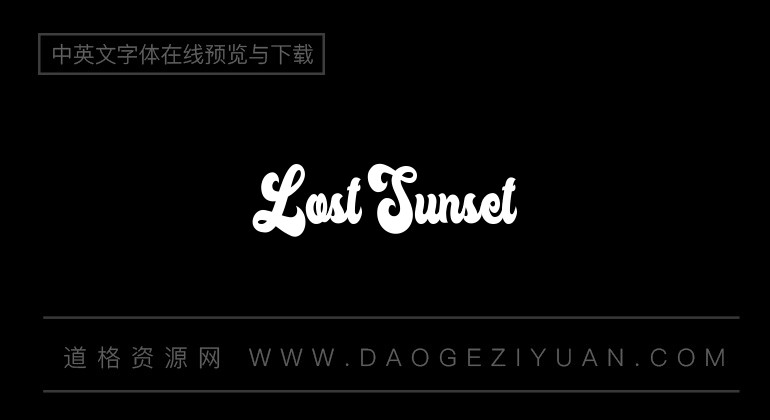
Lost Sunset 是一种非常漂亮的手写风格的字体。它的特点是非常优美的笔画和流畅的线条,非常适合用来设计卡片、海报、标志、书籍封面等。这种字体的字母形状非常有个性,其中有一些字母的形状比传统字体更加独特。此外,Lost Sunset 字体还有一个特点就是它有多种字重可供选择,包括 Regular、Light 和 Bold,因此它可以适应不同的设计需求。总之,Lost Sunset 字体是一种非常优美、独特的字体,非常适合用来设计各种不同类型的作品。内容介绍
Lost Sunset是一款非常不错的手写艺术字体,具有很好的视觉感,适合于文化类的宣传设计、商业类品牌的广告和产品包装设计以及个性化文字排版等较多场景。